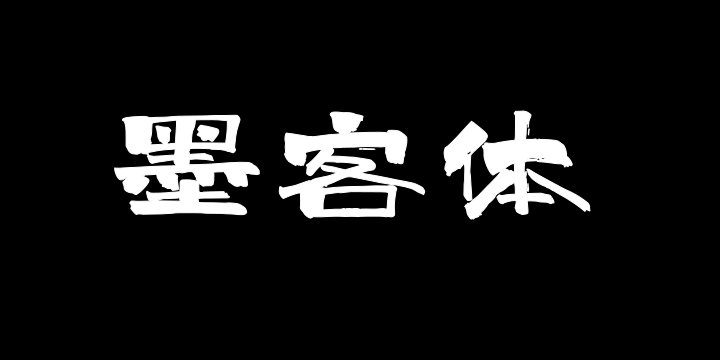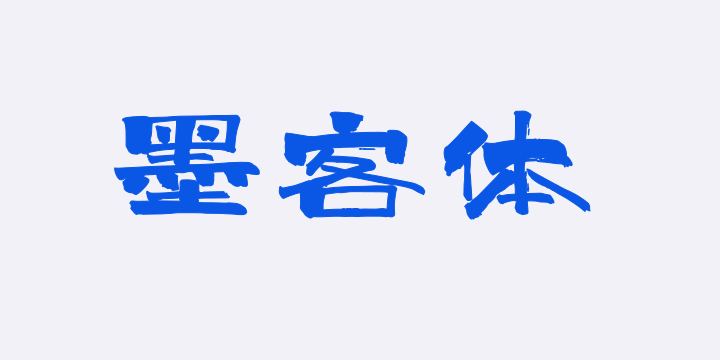
上首墨客体 By 上首造字 商用字体
字体全名: 上首墨客体
铸字厂: 上首造字
设计师: 胡博剑
字体简介: 上首墨客体,笔画粗细变化自然,兼具力量感与柔和度。起笔、收笔的提按顿挫,呈现出独特的笔触感;笔画转折处或方或圆,方折彰显刚劲,圆转蕴含柔美,丰富了字体的视觉层次。通过对字体重心的精准把握,使每个字都具有良好的平衡感;同时,字间布局疏密得当,既保证了整体的和谐统一,又增强了视觉的节奏感。通过对传统书法元素的提取与重构,使字体在视觉上保留了书法艺术的精髓,实现了对中华文化的传承与延续。适用于搭配标志、广告标语、商业广告等高端属性。